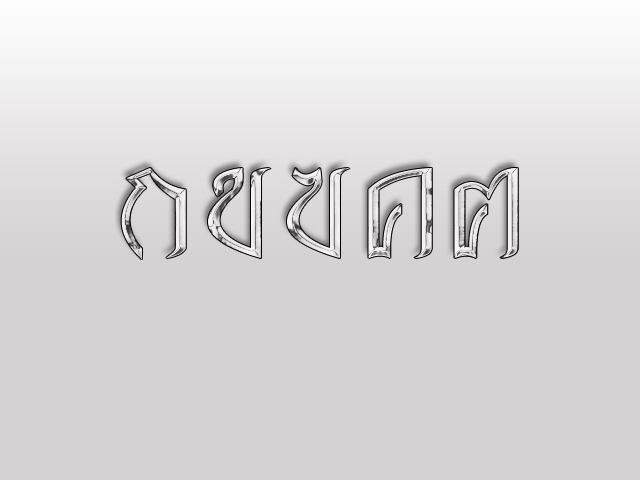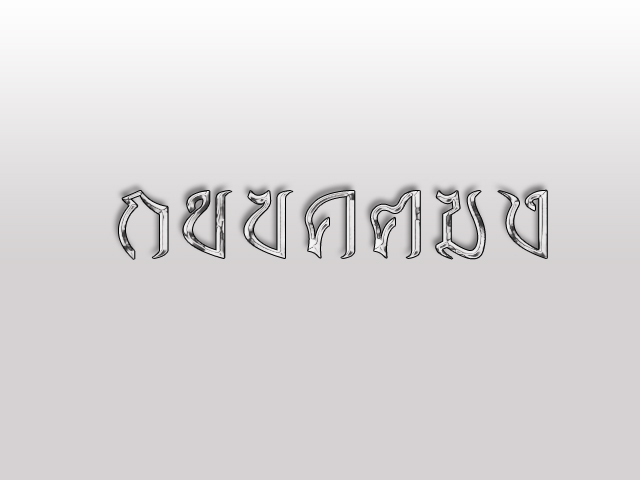
มือใหม่หัดทำฟร้อน
เฮ้อ ในที่สุดก็ออกแบบ(ในสมุด) ครบทุกตัวซักที อิอิ เหนื่อยเหมือนกันน่ะเนี่ย
เอาอีก 2 ตัวมาให้ดูครับ ได้แค่ ก ไก่ กับ ข ไข่ - -* พรุ่งนี้จะทำตัวอื่นต่อ
ชอบ ฃ ฃวด กับ ค ควาย ครับ  :04:
สวยมากครับ โดยเฉพาะตอนใส่ effect  :45:
effect นี่ใช้โฟโต้ช็อป หรือว่าฟอนต์แล็บทำครับ ถ้าฟอนต์แล็บ ทำยังไรเหรอครับ
นั่นมัน effect บน PhotoShop เจ้า FontLab ทำอย่างงี้ไม่ได้หลอก อย่างดีแค่ใส่ลูกเล่นเล็กๆ น้อยๆ เท่านั้น
เงาซะ... อย่างงั้น  :43:
เอฟเฟ็คใช้ โฟโต้ช็อปทำน่ะครับ ถ้าสนใจ เดี๋ยวไว้จะโพสวิธี เซตค่า เลเยอร์สไตล์แบบโลหะเงินให้น่ะครับ
ตอนนี้กำลังเวียนหัว แก้ไปแก้มา ตัว ฅ ฅน ดูแปลก ๆ อ่ะครับ (ส่วนตัวคิดว่าไม่สวย) เลยนั่งแก้ สรุปคือ ป่านนี้แล้ว ยังติดอยู่ที่ตัว ฅ ฅน อยู่เลย  :05:
แหม ถ้าฟอนต์แล็บทำได้ก็คงจะดีซิเนอะ
ผมชอบตัว "ฅ" ผมว่ามันมีเอกลักษณ์ดี
อันนี้คือล่าสุดที่แก้ไขอ่ะครับ ไม่รู้ว่าดีหรือแย่กว่าเดิม  :08:
ผมว่า ฅ. เฉพาะตรงหัวหยักอันเดิมสวยกว่านะ
ฅ อันเดิมสวยกว่า
แบบแรกข้างบนเจ๋งแล้ว
โอ้วสวยจิงๆๆคับผม :42:ทำไงคับอยากทำอะคับสอนผมทำหน่อยได้ปะคับ